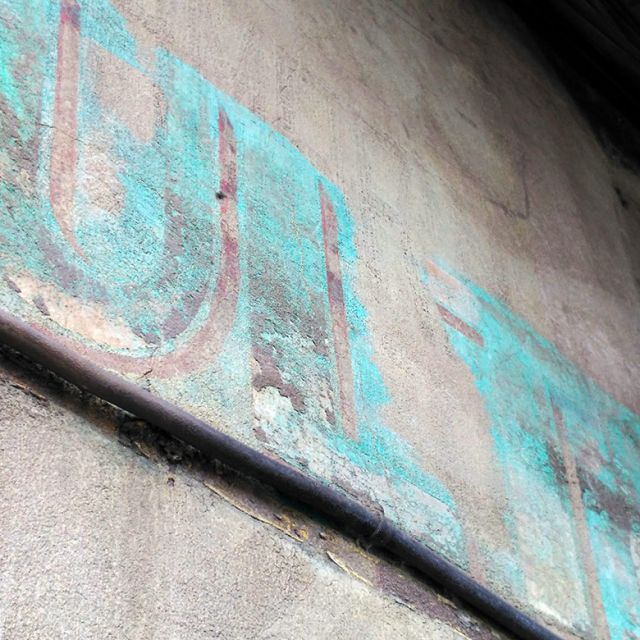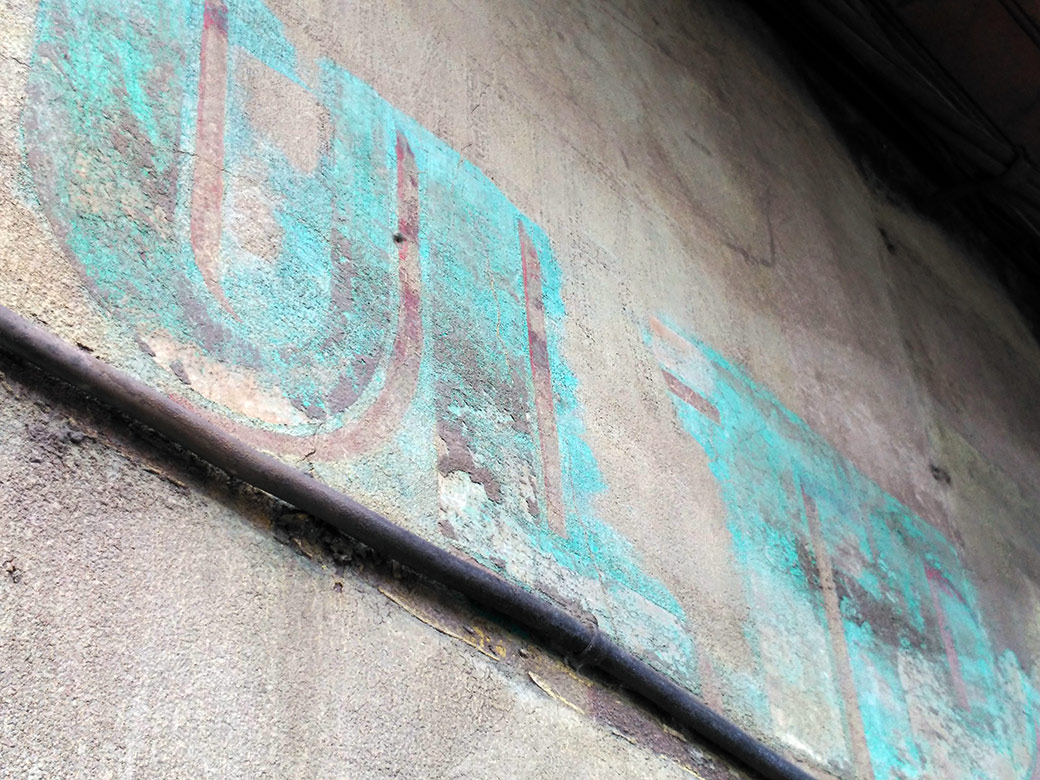
Calle Eduardo García, 30. Santander
1921
Calle Eduardo García, 30. Santander
Estos rótulos permanecen intactos desde la apertura de la tienda en 1921. Así nos lo ha confirmado una vecina, que los dueños no quieren tocarlo. Dada su ubicación, todo parece indicar que fue una de las tiendas del pueblo, de Peñacastillo antes de ser absorbido por Santander con el paso del tiempo.
Gráficamente, se pueden ver como 2 épocas. Una inicial donde, al igual que ocurre con la ferretería Jacobo Díaz, en la propia fachada se exponía lo que se vendía. En pintura negra, con una tipo palo seco se puede leer Ultramarinos, Herrera (Dueños?) o el negativo de Vinos. Después ya con una tipo mayor se taparon, dando paso al que se ve perfectamente «Ultramarinos» hecho en blanco con un efecto de sombra. También en los laterales de la puerta, se puede ver la silueta de como dos escudos, que pueden ser decorativos o pequeños expositores ya que hay algunos agujeros ubicados.
Podríamos hablar de una tercera época, ya que sobre el dintel se observa tapando este 2º rótulo, la forma de lo que puede ser un pequeño cartel – rótulo.